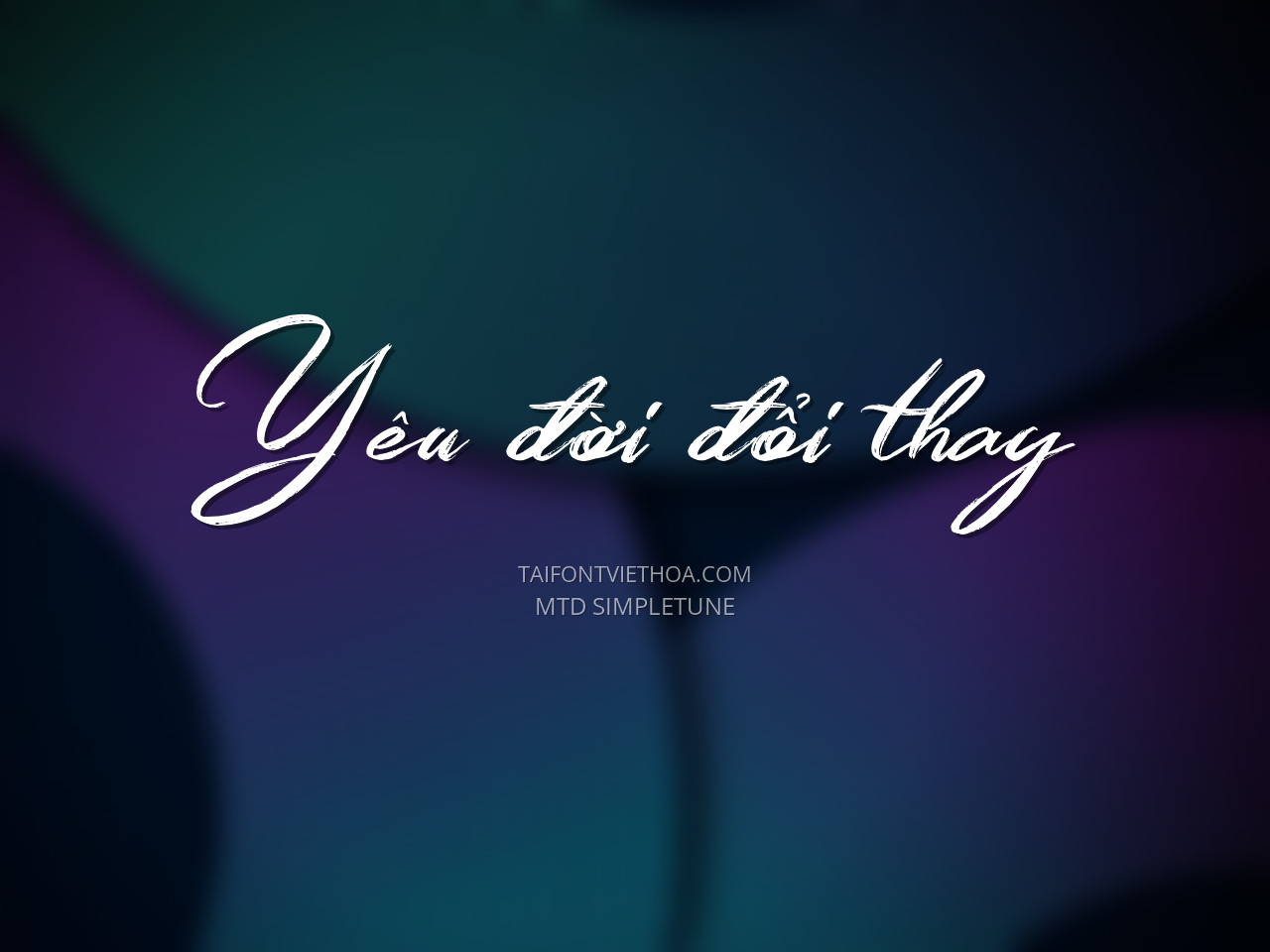
Font việt hóa MTD Simpletune
Tác giả Font: Fhfont
Giới thiệu về font Simpletune
Simpletune là một font script viết tay hiện đại với phong cách nhẹ nhàng, tinh tế và đầy chất thơ. Được thiết kế bởi Motokiwo Type (MTD), font mô phỏng nét bút viết tay mềm mại, mượt mà và có độ nghiêng nhẹ, rất thích hợp cho các dự án thiết kế mang tính cảm xúc, nghệ thuật hoặc hướng đến đối tượng nữ giới. Phiên bản Việt hóa được MTD thực hiện chỉnh chu, hỗ trợ đầy đủ dấu tiếng Việt và hơn 70 ngôn ngữ khác, giúp Simpletune dễ dàng được ứng dụng trong các dự án đa ngữ trên nền tảng in ấn và kỹ thuật số.
Đặc điểm thiết kế và ứng dụng của font Simpletune
Font sở hữu cấu trúc chữ liền mạch với các đường nét thanh mảnh, độ tương phản nhẹ, giúp văn bản hiển thị mềm mại nhưng không quá yếu. Ligatures và swashes được thiết kế tối giản, mang lại sự nhã nhặn và cảm giác thư giãn cho thị giác. Simpletune rất dễ đọc, phù hợp cả ở kích thước nhỏ và trong những thiết kế yêu cầu sự tối giản mà vẫn nổi bật.
Font này lý tưởng cho các ứng dụng như: thiết kế logo cá nhân, typography blog, bao bì mỹ phẩm, thiệp cưới, bìa sách, sản phẩm handmade hoặc poster cảm xúc. Ngành nghề phù hợp gồm: làm đẹp, cưới hỏi, spa, thời trang, quà tặng và truyền thông thương hiệu cá nhân nhẹ nhàng.